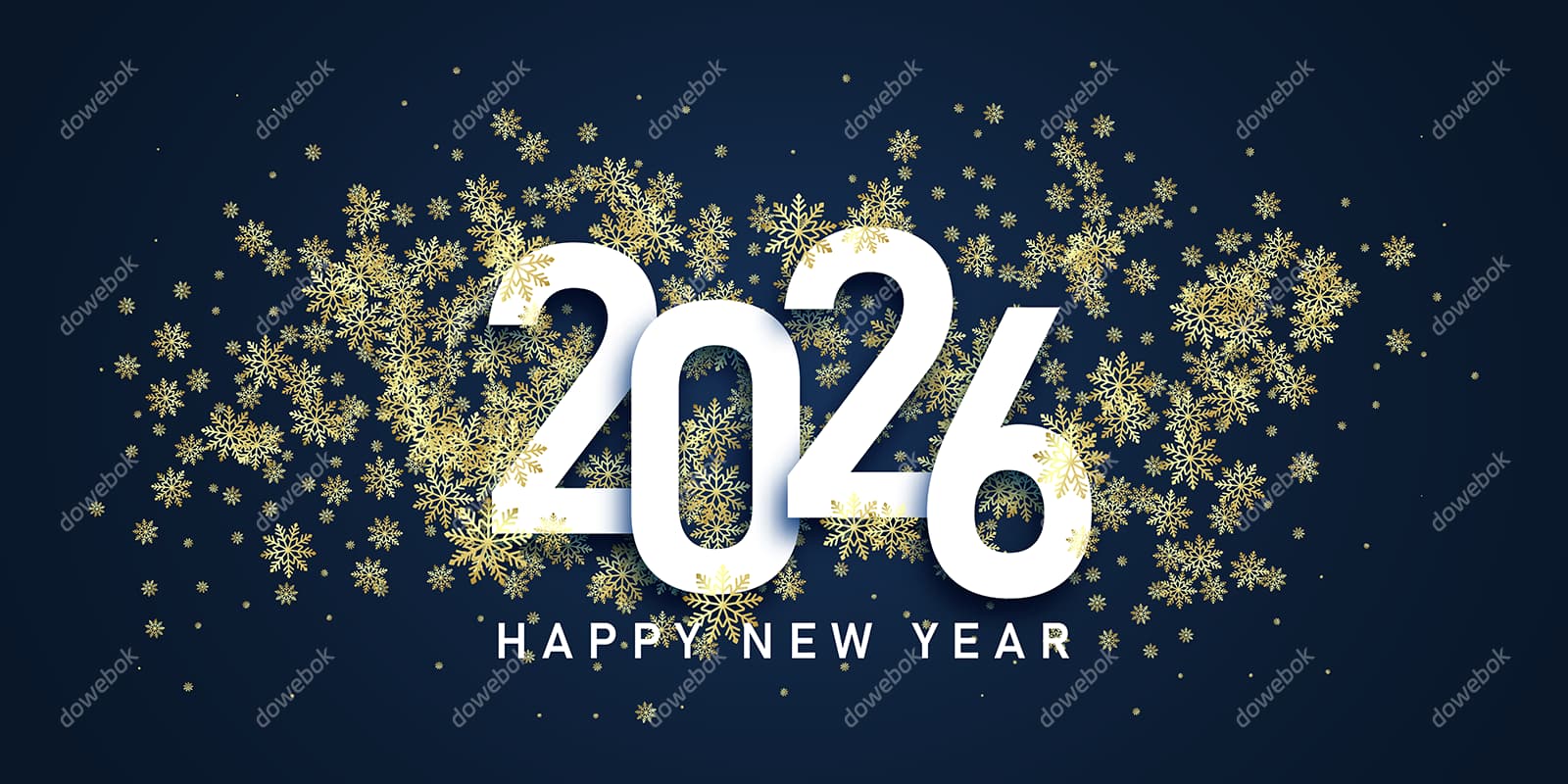
这是一款金色雪花和白色数字设计 2026 新年快乐素材,深蓝背景上,密集的金色雪花层叠铺展,营造出冬日氛围。纯白 “2026” 字体醒目突出,与金雪形成柔和对比,下方衬着简约的 “Happy New Year”。整体以冷调底色 + 暖金雪花元素,既显跨年的冬日温馨感,又用简洁的色彩碰撞透出雅致的节日质感,清新且有氛围。
金色雪花和数字设计 2026 新年快乐矢量素材